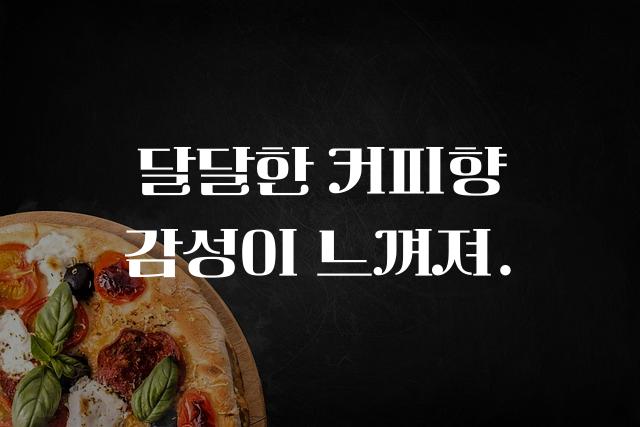
카페24 써라운드
카페24 써라운드는 제목용으로 적합하며, 꽉 찬 고딕 스타일과 둥근 모서리가 특징입니다. 이 폰트는 감성적이면서도 실용적인 디자인을 제공합니다.
부드러운 곡선, 강한 인상 400
이 폰트의 인사이트!
현대적이고 감성적인 표현을 가능하게 하는 목소리
카페24 써라운드은(는) 복실복실, 길고/크고, 기본 고딕, 부드러움, 단단함, 감성적인, 굵은 고딕, 둥근 스타일 계열의 생김새를 가지고 있으며
디지털 광고, 소셜 미디어, 카페 메뉴 등에서 자주 활용되며, 효과적인 메시지 전달에 적합합니다.
이 폰트는 패션/뷰티, 음식/식음료, 라이프스타일 분야에 잘 어울리며,
부드러운, 귀여운, 친근한 느낌을 담고 있는 것이 특징입니다.